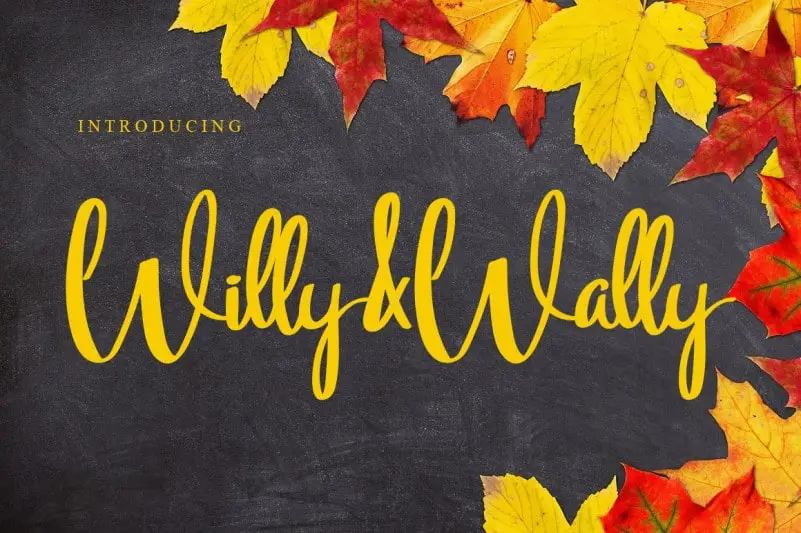
A Willy & Wally Script Font é uma elegante fonte escrita à mão que transmite uma sensação de relaxamento e frescura. Suas linhas naturais e únicas a tornam perfeita para um amplo espectro de designs, permitindo-lhe explorar inúmeras possibilidades criativas sem limitações. Essa fonte tem um estilo único que flui naturalmente nas letras, criando um efeito visual suave e envolvente. Seja você designer ou artista digital, a Willy & Wally Script é uma excelente escolha para seus projetos, pois o seu limite é apenas sua imaginação. Sinta-se à vontade para experimentar os diferentes usos deste fonte em suas próximas criações, seja na composição de letras, em layouts ou até mesmo em ilustrações. Experimente agora a Willy & Wally Script Font da LevinCreative e descubra o potencial que ela pode oferecer.